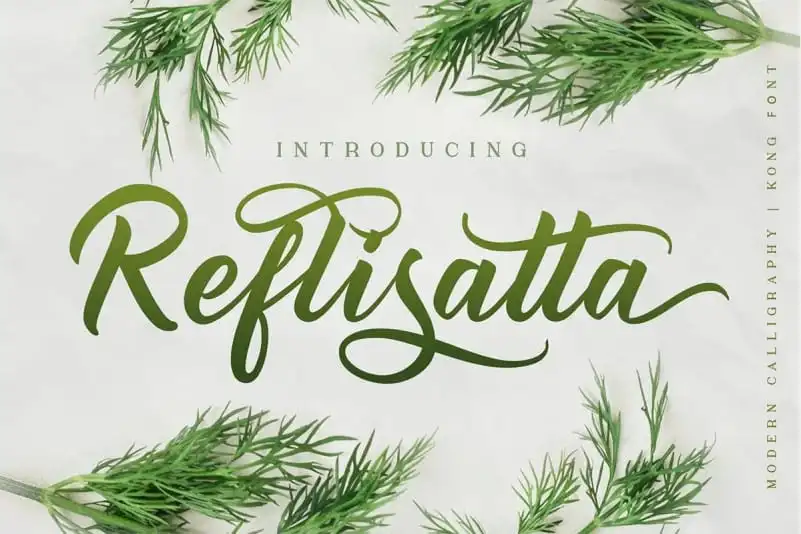
Reflisatta Script Font – Download Grátis
Aqui está uma breve descrição para a página de download da font ‘Reflisatta Script Font’ em português brasileiro: Onde encontrar uma nova fonte script que brinca com as letras, onde estilos sofisticados se unem à delicadeza feminina? Introduzimos Reflisatta Script, uma nova adição na categoria de fontes script. Esta novidade traz ao seu design um ar elegante e audacioso, enquanto mantém o equilíbrio entre a feminilidade e a elegância. Reflisatta é perfeito para quem busca uma fonte que não apenas destaca no papel, mas também flui de maneira natural. Suas características incluem swashes (trabalhadas formas redondas e delicadas nas extremidades das letras), tornando-a ainda mais charmosa. Este tipo especial de fonte é ideal para aplicações em cartões de convite de casamento, rótulos, logotipos, revistas, livros, cartões de felicitação, embalagens, moda, maquiagem, estoque ou qualquer propósito de anúncio. Com Reflisatta Script você pode criar designs impecáveis e cheios de personalidade para seus projetos em diversos formatos. Não perca essa oportunidade de dar um toque especial ao seu trabalho!